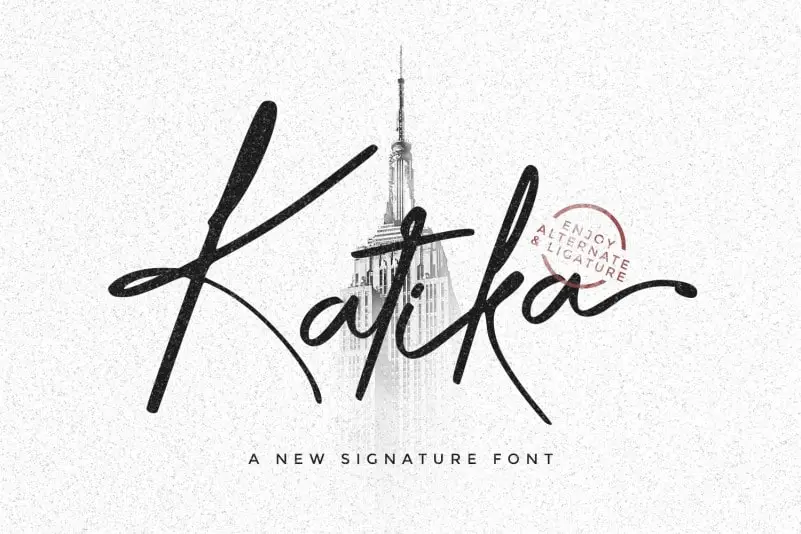
Katika Handwritten Font é uma seleção atraente para qualquer designer que busca adicionar um toque autêntico e moderno às suas criações digitais. Desenvolvida pelo designer dysastudio, essa fonte especializada no estilo de letra escrita representa o melhor da mixagem entre design gráfico tradicional e influências do mundo digital, especialmente das plataformas sociais e anúncios comerciais. Ideal para a criação de marcas, logotipos, designs de casamentos, postagens nas redes sociais, anúncios, embalagens de produtos, designs de produto, etiquetas, fotografias, marqueadores, convites e papéis de presente, Katika Handwritten Font oferece uma mistura única que equilibra a elegância e sofisticação da tipografia tradicional com o charme descontraído dos textos escritos à mão. Suas linhas suaves e caracteres fluidos criam um efeito visual envolvente que certamente se destacará em qualquer projeto onde for aplicada.